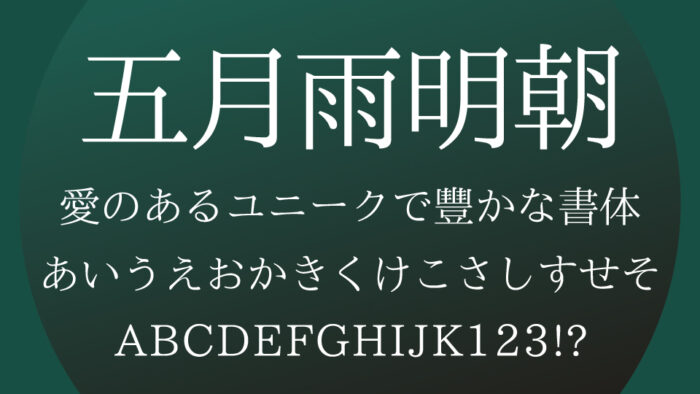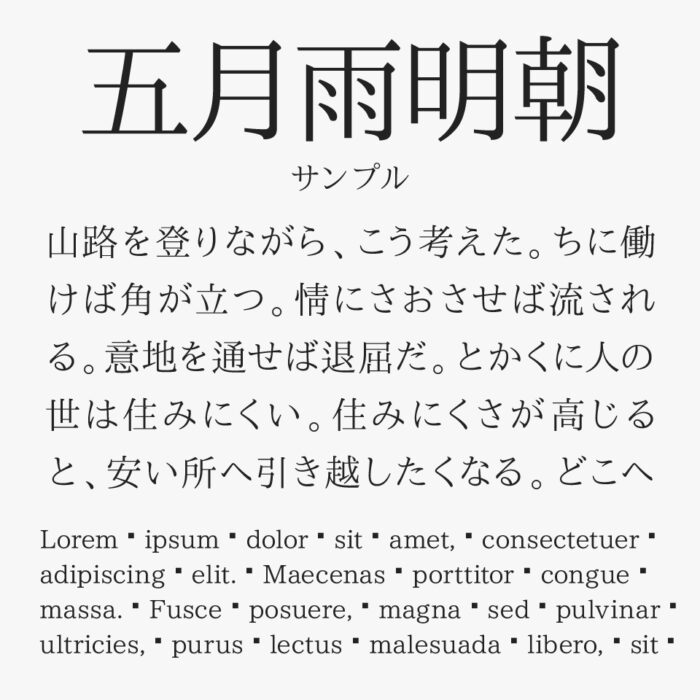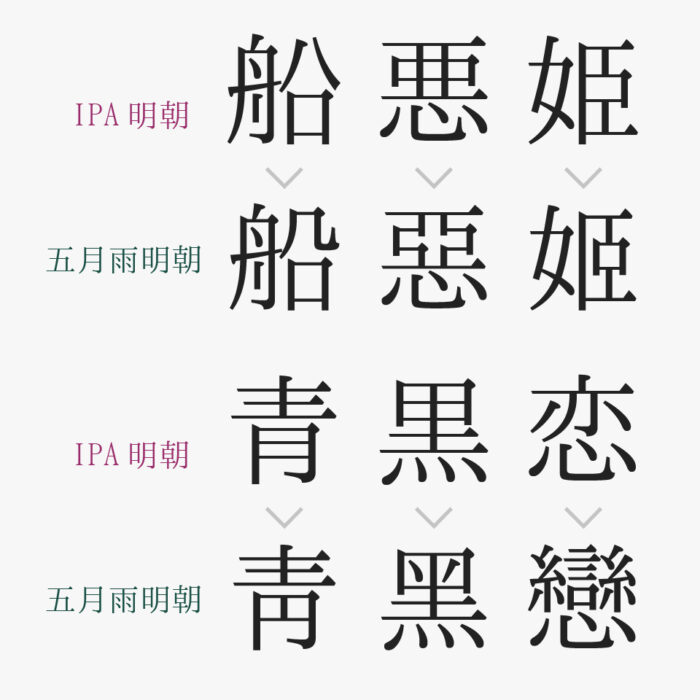
五月雨明朝
五月雨明朝フォントは、IPA明朝フォントをベースとして、旧式明朝印刷体をイメージして制作された明朝体フォントです。
名前の通り、梅雨の情景や湿度を含んだ空気を思わせる、静かで情緒的な佇まいがあります。少しクラシカルで文芸的な印象を与えながらも、現代的な読みやすさも確保されており、優雅さと実用性を両立したフォントです。
正字や旧字を使うことができ、繊細な線と上品な造形が特徴の明朝体で、やわらかく流れるような曲線が印象的です。